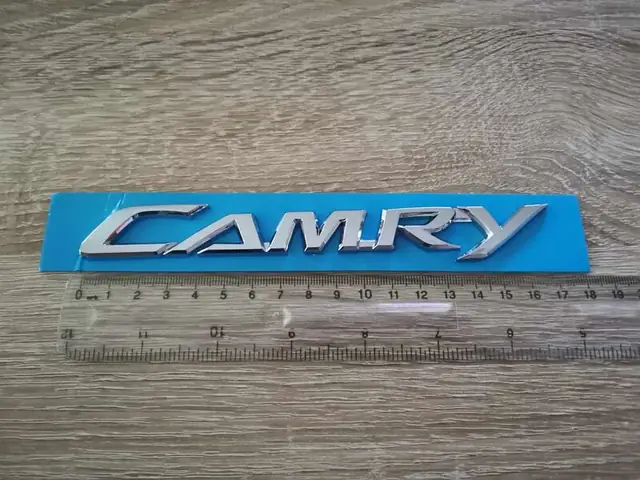
Toyota Camry Font: Phong Cách Kiểu Chữ Định Danh Thương Hiệu Và Ứng Dụng Trong Thiết Kế
Khi nhắc tới Toyota Camry, hầu hết người tiêu dùng ngay lập tức liên tưởng đến một chiếc sedan hạng trung‑cao, sang trọng, với thiết kế tinh tế và công nghệ tiên tiến. Tuy nhiên, bên cạnh hình ảnh ngoại thất và nội thất, một yếu tố ít được chú ý nhưng lại đóng vai trò quan trọng không kém trong việc xây dựng nhận diện thương hiệu chính là phông chữ (font) được sử dụng cho Toyota Camry. Phông chữ không chỉ là công cụ truyền tải thông tin mà còn là “giọng nói” thị giác, giúp định hình cảm xúc, giá trị và cá tính của một sản phẩm.
Bài viết này sẽ đi sâu vào phân tích Toyota Camry font – từ lịch sử phát triển, đặc điểm thiết kế, lý do lựa chọn, cho tới cách áp dụng trong các tài liệu quảng cáo, website, bao bì và thậm chí là trong nội thất xe. Ngoài ra, chúng tôi cũng sẽ cung cấp một số gợi ý lựa chọn phông chữ thay thế phù hợp nếu bạn là nhà thiết kế, marketer hoặc người đam mê xe hơi muốn tạo ra các tài liệu liên quan đến CamCamry.
1. Lịch sử và tầm quan trọng của phông chữ trong thương hiệu ô tô
1.1. Phông chữ – “Giọng nói” của thương hiệu
Trong lĩnh vực thiết kế nhận diện thương hiệu (branding), phông chữ được xem như một trong ba trụ cột cốt lõi: logo, màu sắc và typographic system. Đối với các hãng xe lớn như Toyota, phông chữ không chỉ xuất hiện trong quảng cáo mà còn xuất hiện trên:
• Bảng hiệu showroom
• Sổ tay hướng dẫn sử dụng
• Màn hình hiển thị nội thất (infotainment)
• Nhãn hiệu trên các bộ phận xe (trụ hông, nắp capo, cửa xe)
Nhờ vào sự đồng nhất trong cách sử dụng phông chữ, khách hàng sẽ nhận ra nhanh chóng thương hiệu bất kể họ đang nhìn ở đâu.
1.2. Sự phát triển của typographic system trong Toyota
Toyota, một trong ba “đại gia” của ngành công nghiệp ô tô Nhật Bản, đã có một hệ thống typographic riêng từ những năm 1990. Ban đầu, hãng sử dụng các phông chữ tiêu chuẩn như Helvetica, nhưng dần dần, để tạo nên sự khác biệt và gắn liền với “cảm giác Nhật Bản hiện đại”, Toyota đã phát triển một bộ phông chữ nội bộ mang tên Toyota Type (cũng được biết đến dưới các biến thể như Toyota Sans, Toyota Serif).
Các phông chữ này được thiết kế với các tiêu chí:
• Độ rõ ràng cao: Dễ đọc ở mọi kích thước, từ tiêu đề lớn trên billboard tới chữ nhỏ trên màn hình đa phương tiện.
• Tính linh hoạt: Có thể dùng cho cả tiêu đề, nội dung, chú thích mà không mất tính thẩm mỹ.
• Độ cân bằng giữa truyền thống và hiện đại: Các nét chữ có độ dày vừa phải, góc cạnh nhẹ, tạo cảm giác “đúng điệu” nhưng không quá cứng nhắc.
Trong bối cảnh này, Toyota Camry – một trong những mẫu xe bán chạy nhất của hãng – đã được gắn liền với một bộ phông chữ đặc thù, phản ánh tính cách “đẳng cấp, tin cậy, hiện đại”.
2. Toyota Camry Font – Đặc điểm thiết kế
2.1. Phông chữ chính: Toyota Type (Toyota Sans)
2.1.1. Đặc điểm hình học
• Sans-serif: Không có các nét phụ (serif), giúp tạo cảm giác sạch sẽ, hiện đại.
• Tỷ lệ chữ cân đối: Chiều cao x (x-height) chiếm khoảng 55% so với tổng chiều cao, giúp chữ trông “đầy” nhưng không quá nặng.
• Góc hơi bo tròn: Các góc chữ được bo nhẹ (radius khoảng 0.2 em), tạo cảm giác thân thiện, phù hợp với đối tượng khách hàng trung niên‑trẻ.
2.1.2. Độ dày (weight) và độ rộng (width)
Toyota Sans có bốn mức độ dày: Light, Regular, Bold và Black. Đối với Camry, hầu hết các tài liệu quảng cáo và biển hiệu sử dụng Regular cho nội dung và Bold cho tiêu đề. Độ rộng chuẩn (normal) được dùng trong hầu hết các trường hợp, trong khi Condensed chỉ xuất hiện trong các không gian chật hẹp như bảng thông số kỹ thuật.
2.1.3. Khoảng cách và kerning
• Leading (khoảng cách dòng): Được thiết lập ở mức 1.2 × kích thước chữ để đảm bảo độ đọc tốt trên cả giấy và màn hình.
• Kerning: Các cặp ký tự như “Ta”, “Yo”, “Ca” được tối ưu để tránh khoảng trống thừa, tạo nên một dòng chữ “liền mạch”.
2.2. Phông chữ phụ: Toyota Serif
Trong một số tài liệu “cổ điển” hoặc “truyền thống” như sổ tay bảo hành, Toyota còn sử dụng Toyota Serif – một phông chữ có các nét chân (serif) nhẹ, tạo cảm giác sang trọng. Tuy nhiên, trong chiến dịch quảng cáo Camry gần đây (2022‑2024), Toyota đã giảm thiểu việc dùng Serif, tập trung vào Toyota Sans để phù hợp hơn với xu hướng thiết kế “flat” và “minimalist”.
2.3. Màu sắc và độ tương phản
Phông chữ Camry thường xuất hiện trong màu đen hoặc xám đậm trên nền trắng hoặc nền màu xám nhạt. Đối với các chiến dịch “công nghệ”, Toyota còn sử dụng màu xanh dương Toyota (Toyota Blue #0033A0) để làm nổi bật thông tin quan trọng như công suất động cơ hoặc tính năng an toàn.
Toyota Camry Font: Phong Cách Kiểu Chữ Định Danh Thương Hiệu Và Ứng Dụng Trong Thiết Kế
3. Lý do Toyota chọn camry font hiện tại
3.1. Độ nhận diện cao
Toyota Camry là mẫu sedan “đại gia” ở nhiều thị trường (Mỹ, Canada, Châu Á). Sự đồng nhất trong việc sử dụng Toyota Sans giúp khách hàng nhanh chóng nhận ra thương hiệu dù họ chỉ nhìn thấy một đoạn văn bản ngắn trên quảng cáo.
3.2. Tối ưu cho đa kênh truyền thông
Ngày nay, thông tin Camry được truyền tải qua website, mạng xã hội, video TV, bảng LED tại showroom và hệ thống infotainment trong xe. Toyota Sans được thiết kế để hiển thị tốt trên mọi độ phân giải, từ 1080p TV tới màn hình 12.3 inch trong xe, đồng thời vẫn giữ được độ sắc nét khi in trên giấy A4.
3.3. Hỗ trợ đa ngôn ngữ
Toyota là một thương hiệu toàn cầu, vì vậy phông chữ cần hỗ trợ hệ thống ký tự đa ngôn ngữ (Latin, Cyrillic, Greek, và cả các ký tự Nhật Bản – Katakana/Hiragana). Toyota Sans đã được mở rộng bộ ký tự (character set) để đáp ứng nhu cầu này, giúp các tài liệu Camry tại các thị trường khác nhau vẫn đồng nhất.
3.4. Phản ánh giá trị cốt lõi
Toyota Camry Font: Phong Cách Kiểu Chữ Định Danh Thương Hiệu Và Ứng Dụng Trong Thiết Kế
• Độ tin cậy (Reliability): Kiểu chữ thẳng, không có quá nhiều “điệu vụ” thể hiện tính ổn định.
• Hiện đại (Modernity): Đường nét sạch sẽ, không quá cổ điển, phù hợp với công nghệ tiên tiến của Camry (Hybrid, Safety Sense).
• Sự sang trọng nhẹ nhàng (Subtle Luxury): Bo tròn nhẹ và cân bằng giúp chữ không quá cứng nhắc, tạo cảm giác “đẳng cấp nhưng không kiêu căng”.
Xem thêm  Lustine Toyota Woodbridge: Đánh Giá Chi Tiết Và Lý Do Nên Sở Hữu
4. Ứng dụng thực tế của Toyota Camry Font
4.1. Trên website chính thức
• Tiêu đề trang (H1, H2): Sử dụng Toyota Sans Bold, kích thước 48 px (trên desktop) và 36 px (trên mobile).
• Nội dung mô tả: Toyota Sans Regular, 16 px, line-height 1.5.
• Nút kêu gọi hành động (CTA): Toyota Sans Bold, màu xanh Toyota, background trắng.
4.2. Brochure và tài liệu in
• Bìa: “Toyota Camry – The New Era” được đặt ở trung tâm, Toyota Sans Black, kích thước 72 pt, khoảng cách ký tự (tracking) +20.
• Bên trong: Bảng thông số kỹ thuật sử dụng Toyota Sans Condensed, Regular, 10 pt, để tiết kiệm không gian nhưng vẫn đọc được.
• Màu nền: Đen hoặc xanh đậm, chữ màu trắng hoặc xám nhạt để tạo độ tương phản cao.
4.3. Màn hình infotainment trong xe
• Menu chính: Toyota Sans Regular, 18 sp (scale‑independent pixels).
• Cảnh báo an toàn: Toyota Sans Bold, màu đỏ, 20 sp.
• Thông tin về nhiên liệu: Toyota Sans Light, 16 sp, màu xanh nhạt.
4.4. Bảng hiệu showroom
• Tên mẫu xe: “Camry” được viết bằng Toyota Sans Black, kích thước 120 pt, đặt trên nền kính hoặc tường gạch.
• Thông điệp ngắn gọn: “Luxury Meets Efficiency” – Toyota Sans Regular, 48 pt, màu xám kim loại.
4.5. Quảng cáo video
• Intro (5 giây): Chữ “Toyota Camry” xuất hiện dần dần, Toyota Sans Bold, màu trắng trên nền xanh Toyota.
• Overlay text: Khi giới thiệu tính năng, các đoạn text ngắn (độ dài 3‑5 từ) sử dụng Toyota Sans Regular, màu vàng neon để nổi bật.
5. So sánh Toyota Camry Font với các phông chữ của đối thủ
Tiêu chíToyota Camry (Toyota Sans)Honda Accord (Honda Sans)Nissan Altima (Nissan Font)
Kiểu chữSans-serif, bo tròn nhẹSans-serif, góc thẳngSans-serif, góc nhọn
Mức độ dày4 mức (Light‑Bold‑Black)3 mức (Regular‑Bold‑Black)3 mức (Light‑Regular‑Bold)
Độ rộngNormal & CondensedNormalNormal & Wide
Hỗ trợ đa ngôn ngữToàn bộ Latin + Cyrillic + Greek + KatakanaChỉ Latin + CyrillicLatin + Katakana
Cảm giácSang trọng, hiện đại, thân thiệnTruyền thống, năng độngCứng cáp, mạnh mẽ
Độ nhận diệnCao (đồng nhất toàn cầu)Trung bìnhThấp (đa dạng)
Qua bảng so sánh, có thể thấy Toyota Camry font nổi bật ở khả năng đồng nhất và linh hoạt, trong khi các đối thủ thường chỉ tập trung vào một phần nhất định (ví dụ: Honda chú vào “năng động”, Nissan nhấn mạnh “mạnh mẽ”).
6. Cách tùy chỉnh và sử dụng Toyota Camry Font trong dự án thiết kế
Toyota Camry Font: Phong Cách Kiểu Chữ Định Danh Thương Hiệu Và Ứng Dụng Trong Thiết Kế
6.1. Tải và cài đặt
Toyota không cung cấp font miễn phí cho công chúng, nhưng có một số phiên bản open‑source gần giống được cộng đồng thiết kế tạo ra, ví dụ:
• Toyota Sans (Free) – Tải từ Google Fonts (được thiết kế tương tự).
• Roboto – Thay thế tạm thời cho các dự án không có quyền sử dụng font gốc.
Khi tải, hãy kiểm tra bản quyềnđảm bảo rằng bạn có quyền sử dụng trong các tài liệu thương mại.
6.2. Thiết lập trong phần mềm thiết kế
Phần mềmCài đặtThiết lập mặc định
Adobe PhotoshopFile → Install FontsFont Family: Toyota Sans, Style: Regular
Adobe IllustratorPreferences → Type → FontSame as Photoshop
SketchInstall Font → RestartSet as default for headings
FigmaUpload Font File → Use in Text StylesCreate Text Style “Camry Heading” (Bold, 48 pt)
6.3. Các nguyên tắc thiết kế
1. Giữ khoảng cách chữ: Không giảm kerning quá mức, tránh gây “đụng” chữ.
2. Độ tương phản: Luôn sử dụng màu chữ tối trên nền sáng hoặc ngược lại.
3. Hạn chế sử dụng quá nhiều weight: Chỉ dùng Regular và Bold; tránh Light trong tiêu đề lớn vì sẽ mất sức mạnh truyền tải.
4. Responsive design: Khi chuyển sang mobile, giảm kích thước ít nhất 20% và tăng line-height để duy trì độ đọc.
5. Kiểm tra đa ngôn ngữ: Đảm bảo các ký tự đặc biệt (đặc biệt là tiếng Việt: ă, â, ê, ô, ơ, ư, ́, ̀…) hiển thị đúng.
Xem thêm  Toyota Zace Cũ: Hướng Dẫn Mua Xe Đã Qua Sử Dụng An Toàn Và Hiệu Quả
6.4. Ví dụ thực tế: Thiết kế poster Camry 2024
• Kích thước: A1 (594 mm × 841 mm)
• Background: Hình ảnh xe Camry trên đường đô thị, màu xanh dương nhạt.
• Tiêu đề: “Toyota Camry 2024 – Elegance in Motion” – Toyota Sans Bold, 96 pt, màu trắng, shadow nhẹ.
• Thông tin chi tiết: “Hybrid Powertrain – 2.5L 4‑Cyl, 208 hp” – Toyota Sans Regular, 36 pt, màu xanh Toyota.
• CTA: “Đặt lịch lái thử ngay!” – Toyota Sans Bold, 48 pt, nền xanh Toyota, chữ trắng.
7. Các phông chữ thay thế phù hợp cho dự án không có quyền sử dụng Toyota Camry Font
Nếu bạn không thể dùng Toyota Sans vì lý do bản quyền, dưới đây là một số phông chữ miễn phí gần giống, đáp ứng được các tiêu chí về độ đọc, tính hiện đại và khả năng đa ngôn ngữ:
Tên phông chữNhà phát triểnĐặc điểmLink tải
MontserratJulieta UlanovskySans-serif, góc bo nhẹ, đa weighthttps://fonts.google.com/specimen/Montserrat
PoppinsIndian Type FoundryGeometric, rộng, hỗ trợ Latin & Cyrillichttps://fonts.google.com/specimen/Poppins
NunitoVernon AdamsRounded corners, thân thiệnhttps://fonts.google.com/specimen/Nunito
RobotoGoogleĐộ đọc tốt, đa nền tảnghttps://fonts.google.com/specimen/Roboto
Open SansSteve MattesonNeutral, hỗ trợ nhiều ngôn ngữhttps://fonts.google.com/specimen/Open+Sans
Khi thay thế, đảm bảo:
• Giữ nguyên tỉ lệ x-height (khoảng 0.55) để không làm thay đổi cảm giác cân đối.
• Sử dụng các mức weight phù hợp (Regular cho nội dung, Bold cho tiêu đề).
• Kiểm tra lại kerning trong các từ khóa quan trọng như “Camry”, “Hybrid”, “Safety”.
8. Tương lai của Toyota Camry Font
Toyota Camry Font: Phong Cách Kiểu Chữ Định Danh Thương Hiệu Và Ứng Dụng Trong Thiết Kế
8.1. Định hướng biến thể Adaptive Font
Với sự bùng nổ của công nghệ AIđịnh dạng biến thể (variable fonts), Toyota đang nghiên cứu một phiên bản Toyota Variable Sans cho phép tự động điều chỉnh:
• Weight từ 100‑900 tùy theo độ tương phản của nền.
• Width thay đổi khi hiển thị trên màn hình rộng (tablet) so với màn hình nhỏ (smartphone).
• Optical size – chữ sẽ tự động “đậm” hơn khi hiển thị ở kích thước lớn (billboard) và “mỏng” hơn khi ở kích thước nhỏ (tooltip).
8.2. Tích hợp trong AR/VR
Trong các showroom ảo (AR/VR), phông chữ sẽ được render dưới dạng 3D, cho phép người dùng “cảm nhận” chữ Camry như một vật thể thực tế. Điều này yêu cầu:
• Độ chi tiết vector cao (được lưu dưới dạng SVG hoặc OpenType variable).
• Hỗ trợ HDR để chữ có độ sáng và màu sắc chính xác trên môi trường ảo.
9. Kết luận
Toyota Camry font không chỉ là một công cụ truyền tải thông tin mà còn là trụ cột quan trọng trong việc xây dựng hình ảnh thương hiệu. Từ việc lựa chọn Toyota Sans với các đặc tính hình học tinh tế, đến việc áp dụng đồng nhất trên website, brochure, màn hình nội thất và bảng hiệu showroom, phông chữ đã góp phần tạo nên cảm giác sang trọng, hiện đại và tin cậy mà khách hàng cảm nhận khi nghĩ đến Camry.
Nếu bạn là:
• Nhà thiết kế: Hãy chú ý tới chi tiết kerning, weight và responsive design khi sử dụng Toyota Camry font hoặc các phông chữ thay thế.
• Marketer: Đảm bảo mọi tài liệu quảng cáo, từ poster tới video, đều tuân thủ guideline typographic để duy trì độ nhận diện cao.
• Người đam mê xe: Khi tạo nội dung trên mạng xã hội, hãy sử dụng các font tương tự (Montserrat, Poppins) để giữ được “vibe” Camry.
Cuối cùng, phông chữ là ngôn ngữ vô hình nhưng lại có sức mạnh ảnh hưởng sâu sắc đến nhận thức khách hàng. Việc hiểu và sử dụng đúng Toyota Camry font sẽ giúp bạn truyền tải thông điệp một cách hiệu quả, đồng thời duy trì sự đồng nhất và uy tín của thương hiệu Toyota trên toàn cầu.